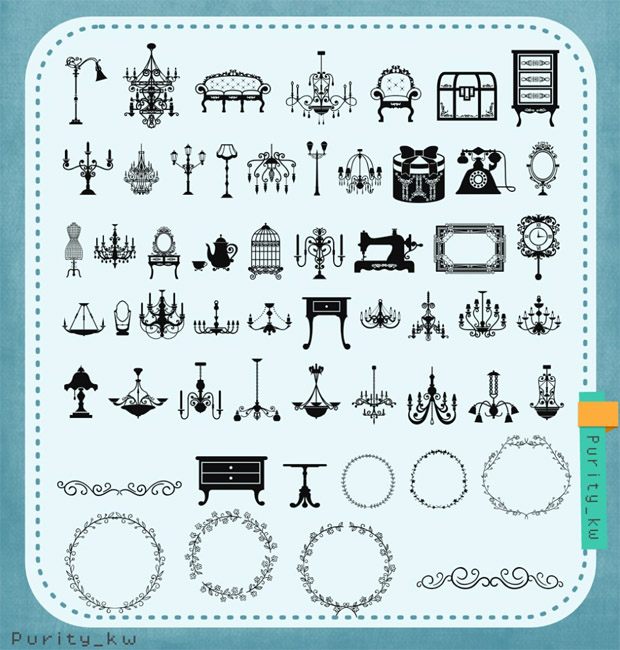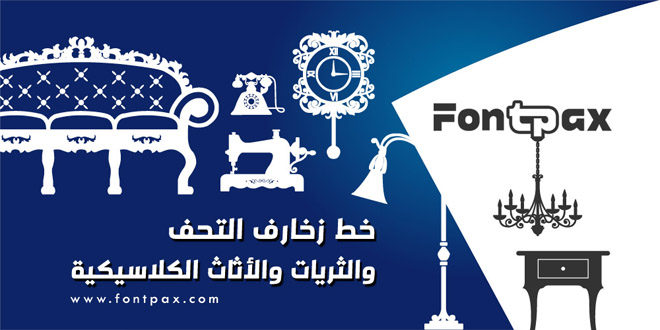
خط زخارف التحف والثريات والأثاث الكلاسيكية .. من تصميم وتركيب الأستاذة النقاء Purity_KW، يحتوي ملف الخط على مخطوطات زخارف كلاسيكية رائعة حول الأثاث القديم والثريات وبعض التحف والمقتنيات الجميلة، ويعمل الخط بالحروف الإنجليزية الكبيرة والصغيرة، وهو متاح للتحميل المجاني الآن.